Безопасная типографика: как избежать двусмысленных указателей
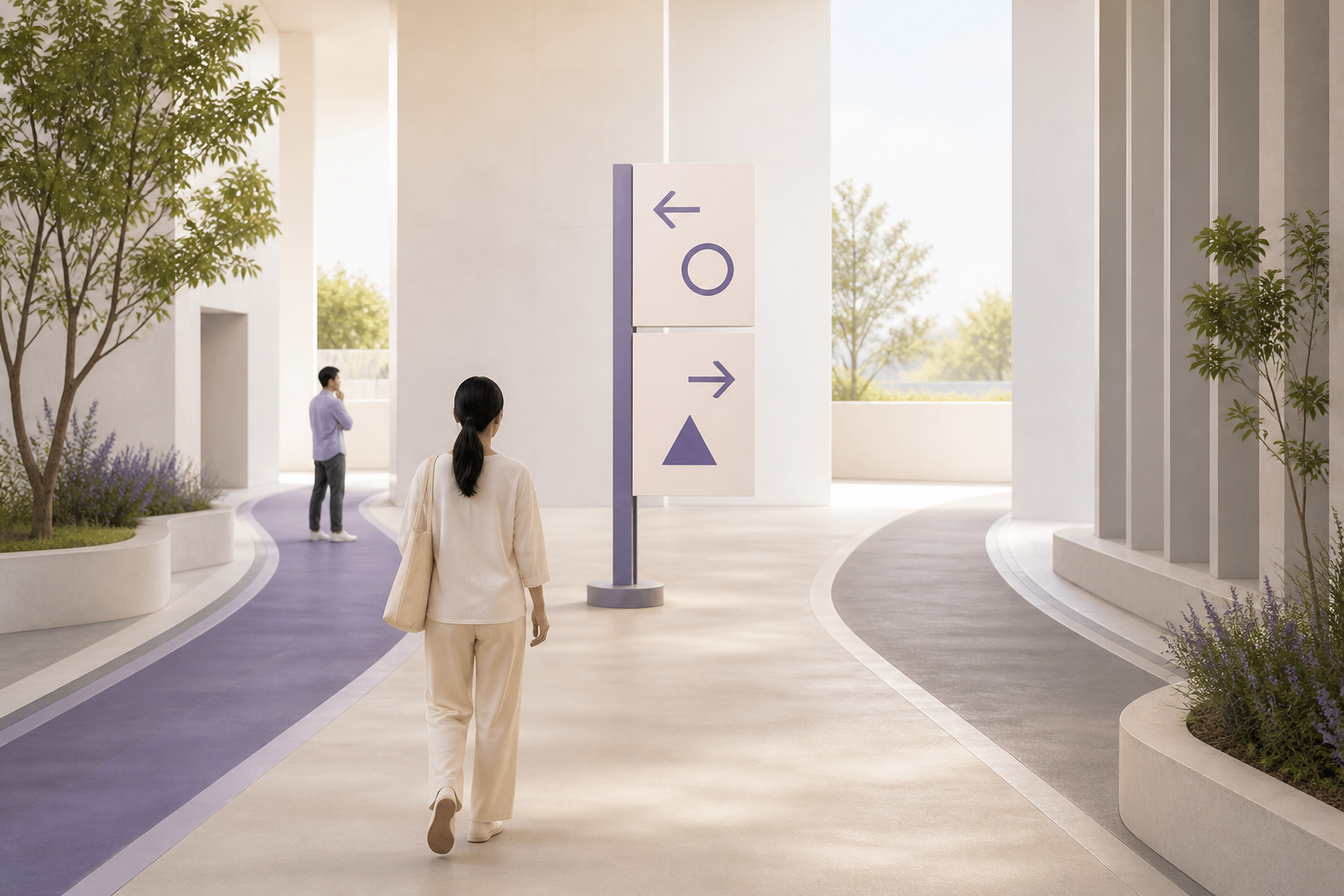
Безопасная типографика делает указатель однозначным: человек быстро распознаёт буквы, понимает направление и не путает текст с похожим словом или символом. Для этого нужно одновременно проверить форму кириллических знаков, размер, интервалы, контраст, расположение стрелок и поведение надписи на реальном расстоянии просмотра.
Почему указатель может читаться двусмысленно
Двусмысленное чтение возникает не только из-за неудачного шрифта. Надпись может терять смысл, если буквы сливаются, стрелка находится слишком далеко от подписи, строка разбита в неожиданном месте или фон снижает контраст. В результате пользователь тратит время на повторное чтение, выбирает неверный маршрут или останавливается в месте, где нужно двигаться дальше.
Для указателя важна не декоративность сама по себе, а скорость и точность распознавания. В обычном заголовке читатель может вернуться к началу строки, а в навигации такой возможности часто нет: решение принимается на ходу, под углом, при неравномерном освещении или среди других визуальных объектов.
Три уровня читаемости навигационного текста
Разборчивость указателя удобно проверять на трёх уровнях. Сначала оценивают форму отдельных знаков, затем чтение слов и строк, а после этого — понимание всей системы. Даже хороший шрифт не спасёт макет, если текст слова читается, но непонятно, к какой двери или стрелке он относится.
- Буква: различаются ли похожие знаки, например О и цифра 0, З и цифра 3, И и П в конкретном начертании.
- Слово: не сливаются ли соседние буквы, не теряются ли диакритические знаки и мягкий знак.
- Строка: легко ли пройти её взглядом без неожиданного переноса или неоднозначного разрыва.
- Система: понятно ли, куда ведут стрелка, цвет, пиктограмма и подпись вместе.
Как выбрать шрифт для указателей
Для навигации обычно подходят начертания с ясной конструкцией букв, умеренной плотностью и устойчивой формой в разных размерах. Слишком тонкие штрихи теряются на расстоянии, чрезмерно контрастные буквы хуже переносят слабое освещение, а декоративные детали могут менять силуэт слова. Выбор нужно делать не по образцу одной крупной буквы, а по полному набору фраз, которые действительно появятся на указателях.
- Проверьте кириллический набор, а не только латиницу из презентации шрифта.
- Выберите начертание с различимыми формами О, С, Е, З, И, Й, Л и Д.
- Сравните обычное, полужирное и жирное начертания на реальном фоне.
- Откажитесь от чрезмерно узких букв, если надпись должна читаться сбоку или издалека.
- Проверьте, не исчезают ли внутренние просветы букв при уменьшении.
Почему кириллицу нужно проверять отдельно
Латинский образец не показывает, как шрифт работает с русским текстом. В кириллице есть собственные характерные формы, высоты и соединения, поэтому надпись «ВЫХОД», «ЛИФТ», «КАССА» или «ПЕРЕХОД» следует тестировать целиком. Отдельно проверьте буквы с диакритикой: Й, Ё и знак в Ъ или Ь могут потерять читаемость при плотном наборе.
Особое внимание нужно уделить словам, где одна буква заметно меняет смысл. Различие между «ВСЕ» и «ВСЁ», «ПЕРЕЕЗД» и другими похожими по силуэту сочетаниями показывает, почему точки, двоеточия, кавычки и другие знаки нельзя считать второстепенными. Если знак важен для понимания, он должен сохранять форму и не сливаться с соседними элементами.
Интервалы, кегль и контраст: настройка без догадок
Размер текста выбирают не по привычному кеглю, а по сценарию просмотра. Указатель в коридоре читают с близкого расстояния, табличку над входом — с другого, а дорожный или уличный знак может рассматриваться в движении. Поэтому один и тот же шрифт нужно проверять в натуральном масштабе, с предполагаемой точки обзора и при максимально похожем освещении.
Межбуквенный интервал должен поддерживать цельные слова. Слишком плотный набор превращает соседние формы в одно пятно, а чрезмерный трекинг разрушает узнавание слова по общему силуэту. Начните с настроек шрифта, затем внесите небольшую корректировку и сравните несколько вариантов на длинных словах, а не только на коротких подписях.
Контраст — это не только сочетание чёрного и белого. На восприятие влияют цвет фона, материал поверхности, блики, подсветка, расстояние между текстом и рамкой. Приглушённый текст на фактурном фоне может выглядеть выразительно в макете, но потерять форму в реальном пространстве. Фон должен помогать буквам, а не конкурировать с ними.
Стрелка и текст должны образовывать одну команду
Навигационная стрелка не является самостоятельной иллюстрацией. Пользователь должен мгновенно понять, к какой надписи она относится и в каком направлении указывает. Не отделяйте стрелку большим пустым промежутком, не помещайте её между двумя равнозначными подписями и не меняйте логику расположения от таблички к табличке.
Вывод: ясность важнее декоративного эффекта
Безопасная типографика строится на последовательной проверке: сначала формы букв и кириллица, затем интервалы, контраст, стрелки, масштаб и реальный сценарий движения. Хороший указатель не заставляет пользователя останавливаться и угадывать смысл — он быстро сообщает, что искать и куда идти.